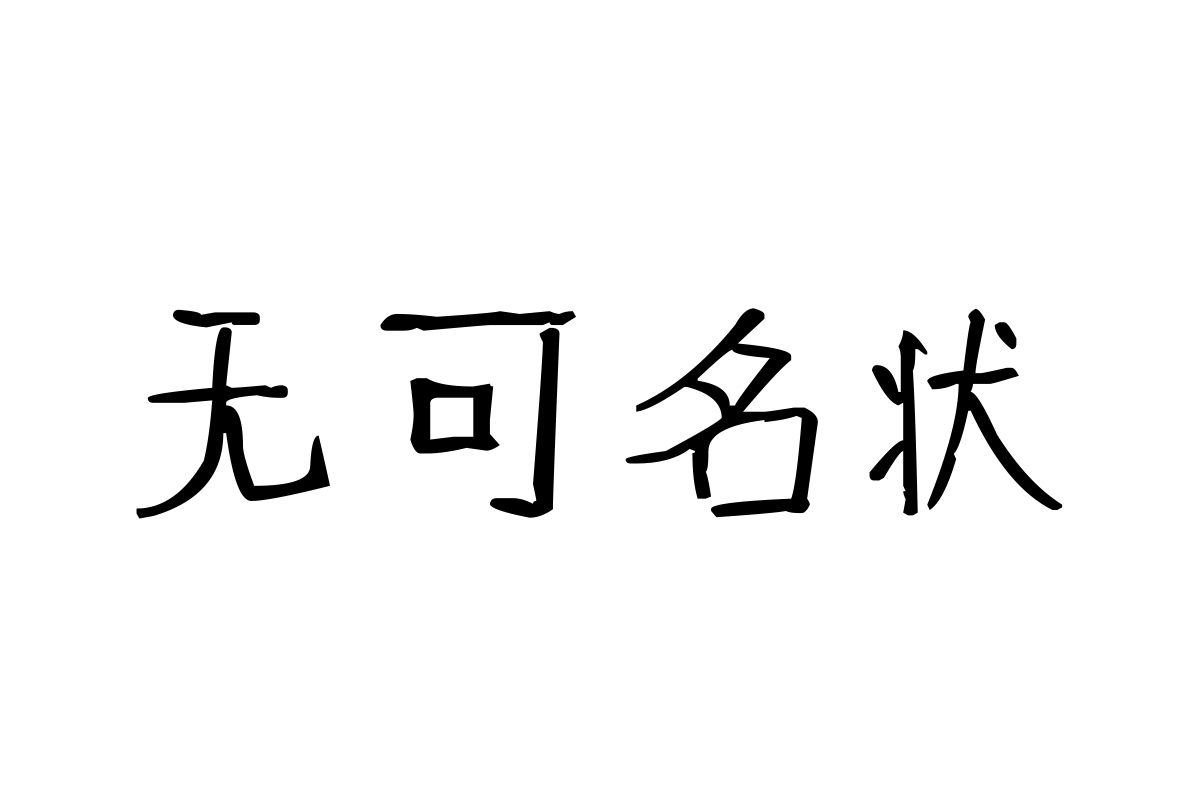
汉标爱僮体是一种具有独特魅力的中文字体,它以优雅、流畅的线条和精致的细节为特点,给人一种宁静、和谐的感觉。这种字体的设计灵感来源于传统的书法艺术,通过巧妙的笔画组合和独特的结构布局,展现出一种独特的美感。
汉标爱僮体的特点在于其精细的笔画处理和丰富的变化性。每个字符都经过精心雕琢,线条流畅而有力,既符合汉字书写的基本规则,又不失个性和创意。这种字体的字形结构严谨,线条粗细适中,既适合正式场合的庄重氛围,又能够适应日常书写的便捷需求。
除了美观大方,汉标爱僮体还具有较强的可读性和实用性。由于每个字的笔画都经过精心设计,因此无论是在印刷还是电子屏幕上,都能够清晰地展现出来,确保信息的准确传递。同时,这种字体也非常适合用于标题、正文等需要强调的部分,能够有效地吸引读者的注意力。
总之,汉标爱僮体是一种集美观、实用于一体的中文字体,它以其独特的魅力和风格,为现代设计提供了更多的选择和可能性。无论是用于书籍、杂志、广告还是其他媒体,汉标爱僮体都能够展现出其独特的风采和价值。